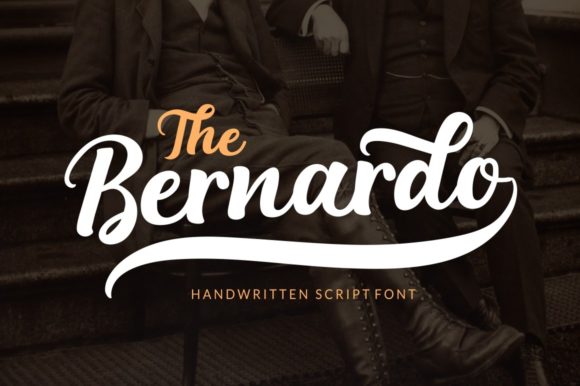
Bernardo - это великолепный и плавный рукописный шрифт, созданный для придания стильности вашим заголовкам и логотипам.
Этот шрифт читается как сильный, уверенный и динамичный и может добавить тонны ностальгического характера в ваши проекты.